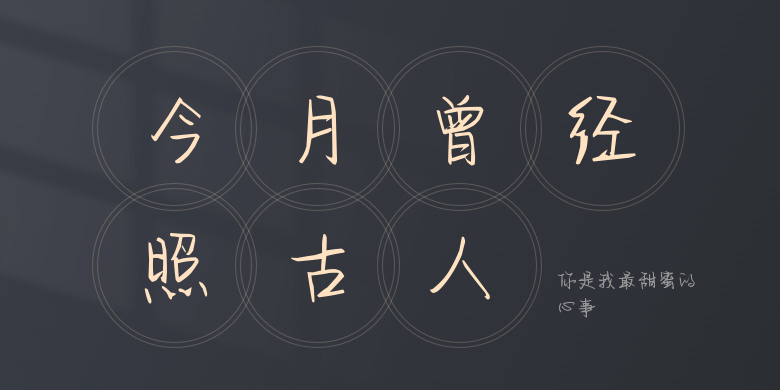
你是我最甜蜜的心事
你是我最甜蜜的心事,这款字体结构工整、笔画清晰,兼顾美观与易读性,适用于标题、正文、海报、包装、LOGO 等多种场景。字形优雅稳定,风格百搭耐看,适配日常排版与创意设计,让文字呈现更舒适、更具质感。你是我最甜蜜的心事一笔一画,皆是细节,以均衡的比例、流畅的线条打造舒适视觉体验,字形端正大气,风格简约现代。无论是商业设计、品牌宣传还是日常排版,都能轻松驾驭,让文字更有格调与力量。你是我最甜蜜的心事字体下载。